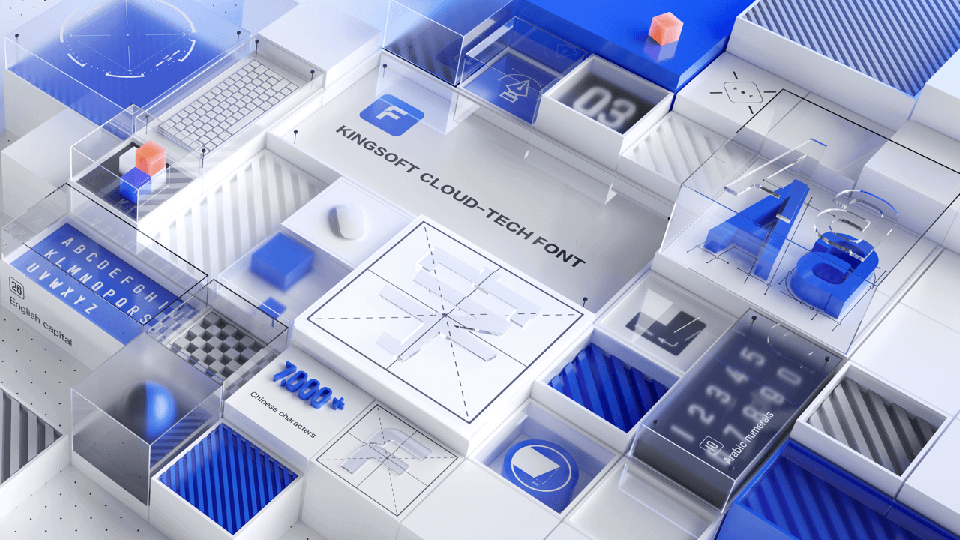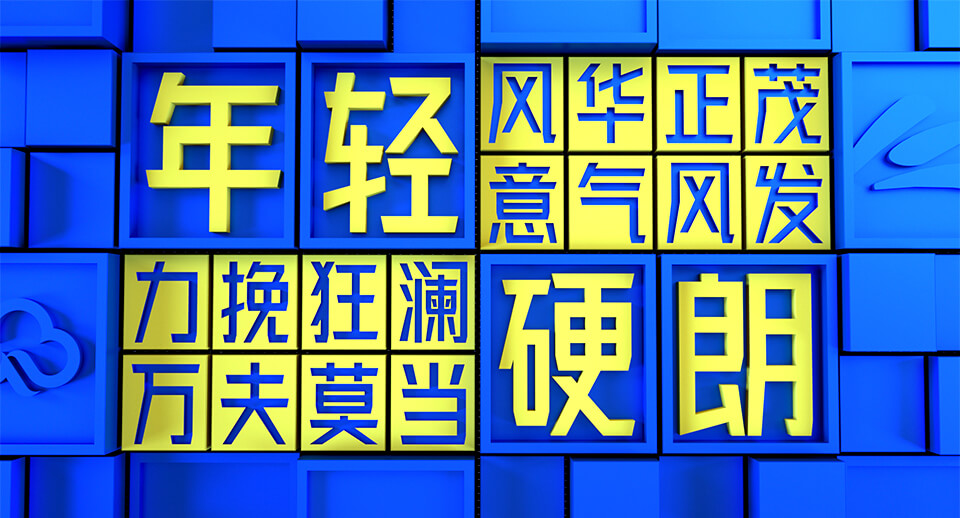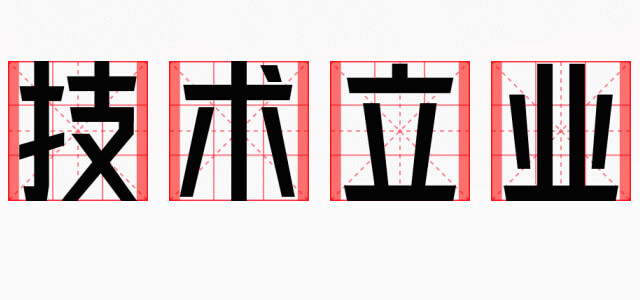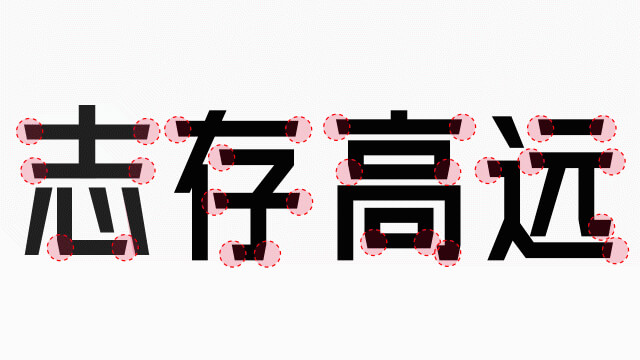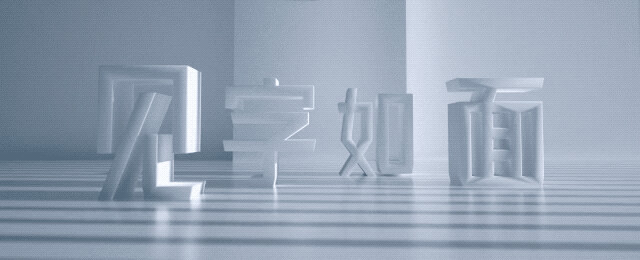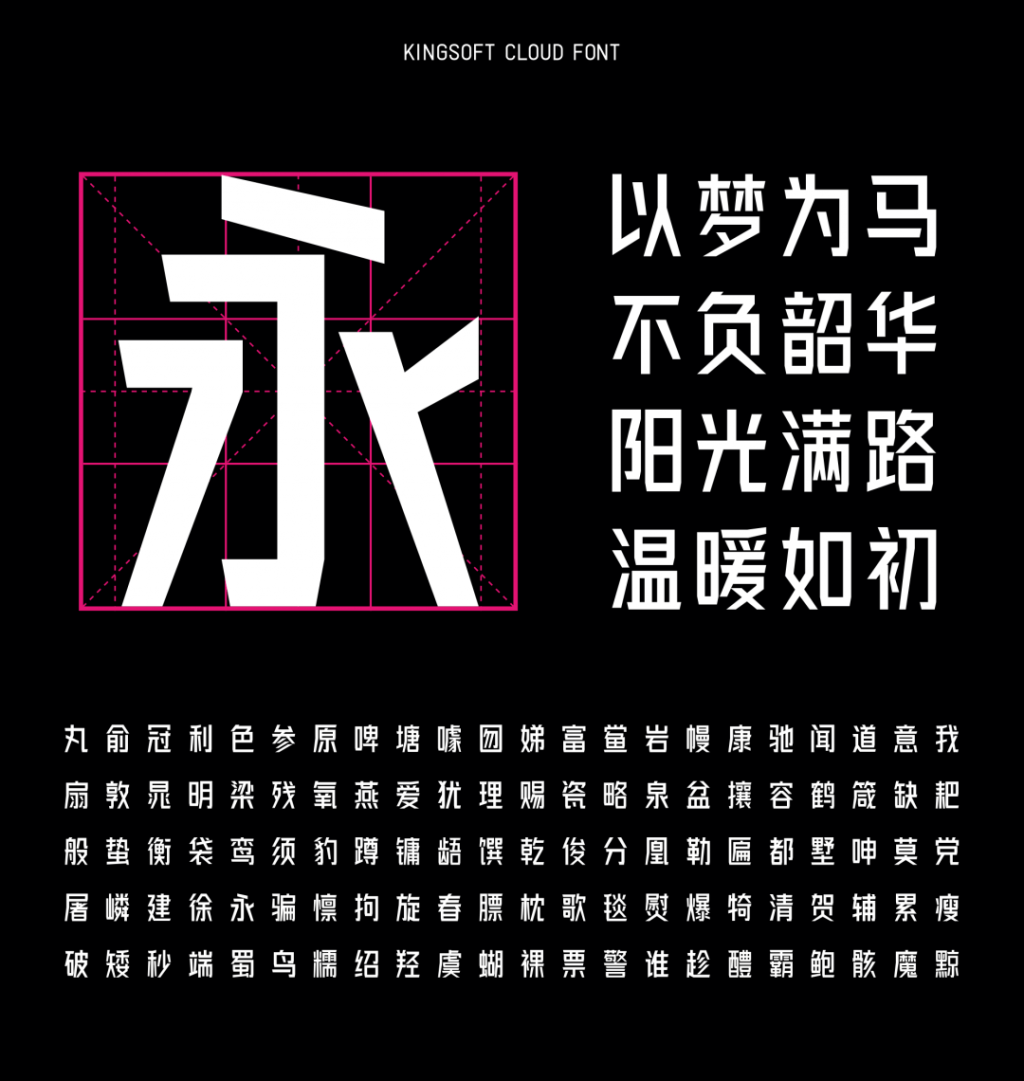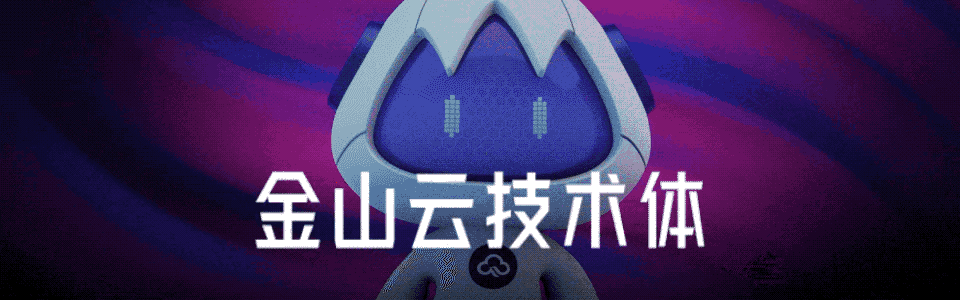
金山云技术体:金山发布首款原创字体 全渠道免费商用!新字体发布
33年前,金山软件因“字”而生。
33年后,金山发布首款原创字体库。
金山云UED设计团队,历时四年,逐点逐字,匠心设计。
“金山云技术体”是一款无衬线体,提供一种标准版字重,文字参照GB2312简体中文编码字符标准。包含国标一级、二级字库汉字6763个,外文及数字符号804个,总字符数7567个。
01 设计理念
字体在整体造型设计上,风格偏向年轻、硬朗、具有活力。
02 字体设计
重新定义1:0.84的字宽比例,设计了整体、左右、上下等搭配方法。让比划多的字与少的字,放在一起看尽量协调,减少视觉疏密感。
笔画
为了打破常规黑体的生硬感,我们选择了最复杂的设计方案,字体的笔划设计根据整字权重划分粗细进行搭配。
修饰
在笔划的衔接和末端处,使用了12度的倾斜设计。
03 字体生态